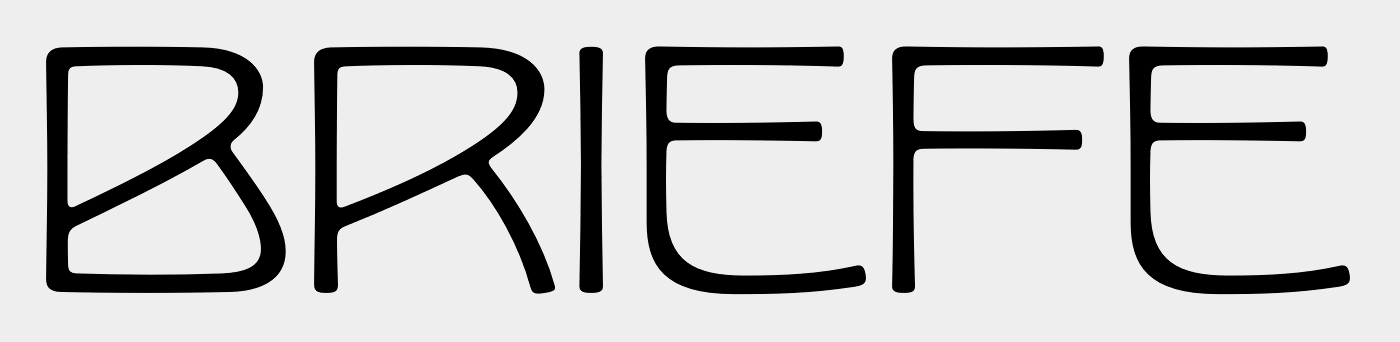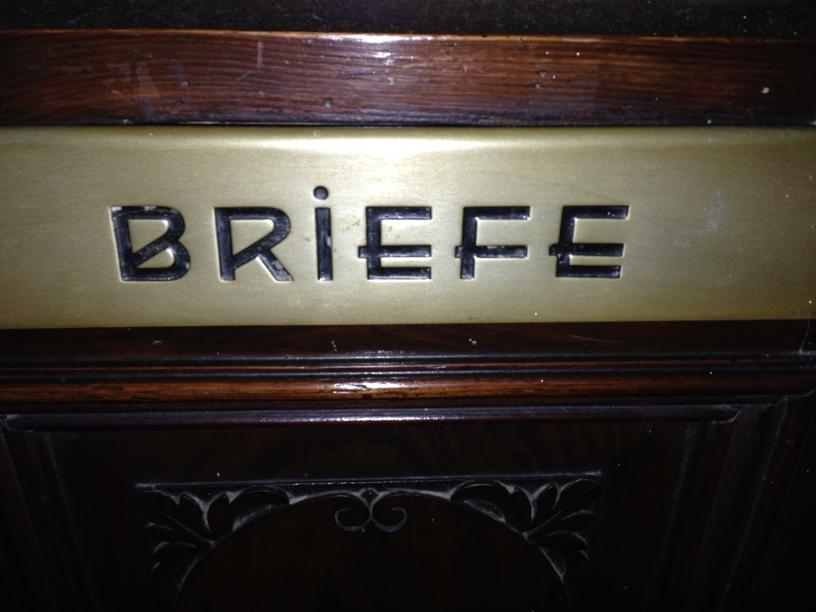
Suche diese Schriftart (Briefkasten-Gravur)
ich bin ein Gravuer aus Erfurt und ein Kunde von mir möchte ein Schild graviert haben mit dieser Schriftart oder so ähnlich. Kann mir jemand vielleicht sagen, was das für eine Schrift ist. Die Seite "WhatTheFont?" hat die Schrift nicht erkannt.
Annähernd in die Richtung:
"Vienna" könnte ein geeignetes Stichwort zur Suche sein, evtl. auch "Art Nouveau". Wobei es die gesuchte Schriftart nicht unbedingt digital geben muss.